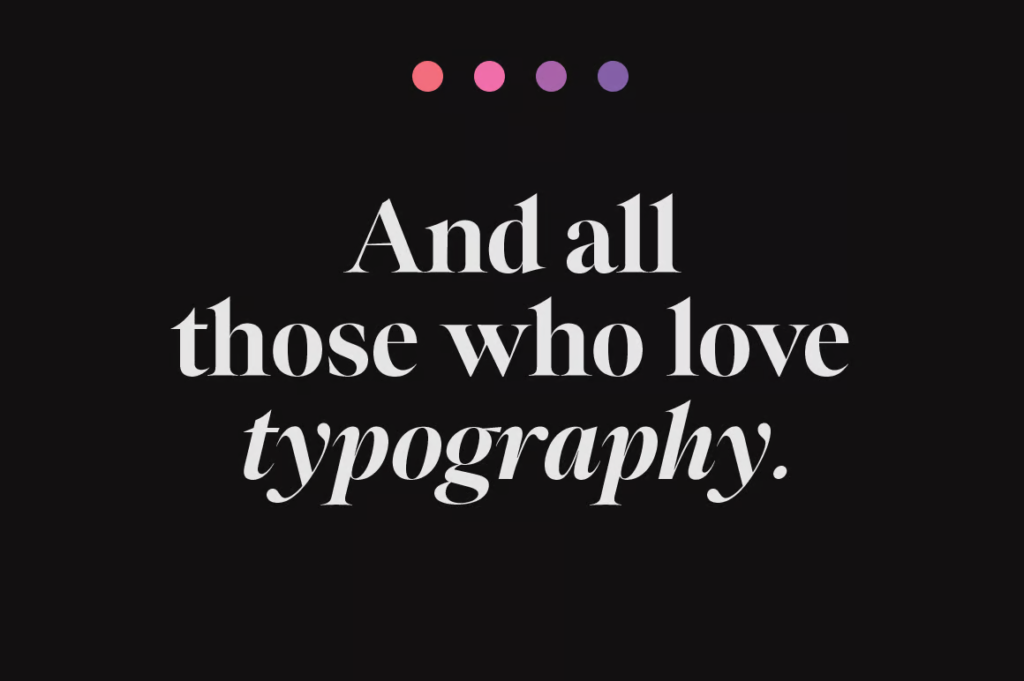
Addington CF serif font family
Description de Addington CF serif font family
Fiable et professionnel en surface, Addington CF s’ouvre et prend vie avec son caractère et son souci du détail. Belle mais pratique – une police polyvalente avec des éléments de calligraphie, des empattements traditionnels et de nouvelles idées – Addington est une police d’empattement incontournable. Excellent pour les textes grands et petits, avec 6 graisses, italiques et fonctionnalités OpenType.
Sept poids
Ensembles romains et italiques
Fonctionnalités OpenType avancées
alphabet latin